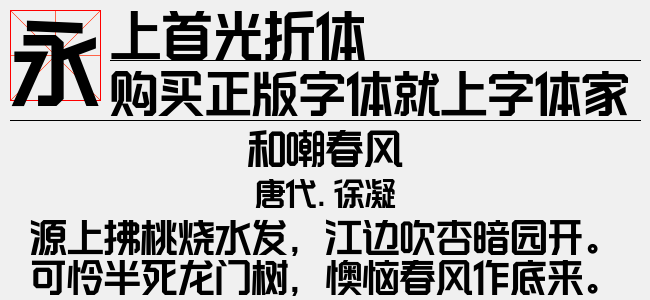
上首光折体
字体作者:上首造字
字体名称:上首光折体
字体家族:上首造字
书体类型:手写/印刷类
字体公司:上首造字
上首光折体
上首光折体,简体中文约6763字,字体横竖笔画粗细差距不大,使其显得均衡,稳重;字体笔画交汇处做了平切转折处理,让其本身具有折叠感;每个笔画都是直线式做法,使其端正;整体上字体比较方正统一,很具稳重大气、刚正不阿的字体特色。适用于搭配标志、广告标语、商业广告等高端属性。